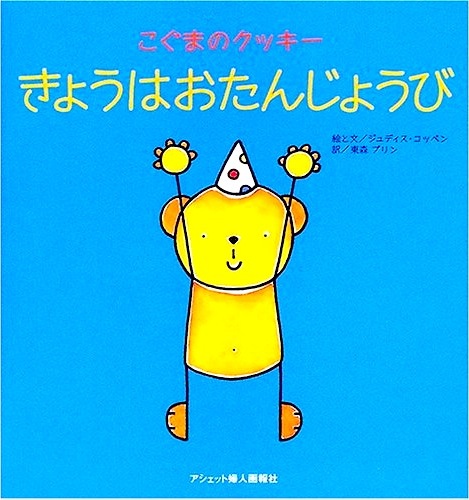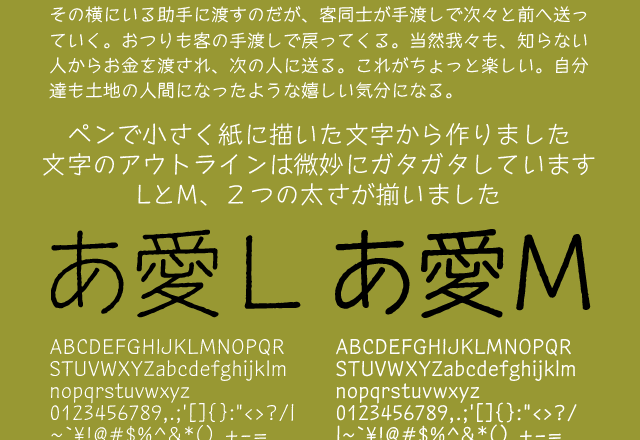
セプテンバーは、細いペンを使って丁寧に書かれた手書きフォントです。文字の輪郭が微妙にデコボコしていて、手書きの風合いがあります。親しみやすく、読みやすい仕上がりになっています。
セプテンバーシリーズのフォント使用例
看板やチラシ、雑誌、絵本、テレビやCM、アニメ、ゲームなど幅広い場面で使われています。使用例一覧が紹介されています。